Oye, lo entiendo—los errores tipográficos en tipografía pueden hacer que tus diseños parezcan poco profesionales y difíciles de leer. Si alguna vez te has sentido frustrado por fuentes que no combinan o espaciados desordenados, no estás solo. Por suerte, si te quedas, descubrirás consejos simples para evitar errores comunes y hacer que tu texto se vea nítido y limpio.
Sigue leyendo, y aprenderás a elegir las fuentes adecuadas, crear una jerarquía visual clara y ajustar detalles como el espaciado y la alineación. Estos trucos fáciles ayudarán a que tu texto se destaque sin complicaciones ni confusiones.
Vamos a lo básico para que tu tipografía se vea pulida y atractiva desde el inicio hasta el final.
Conclusiones clave
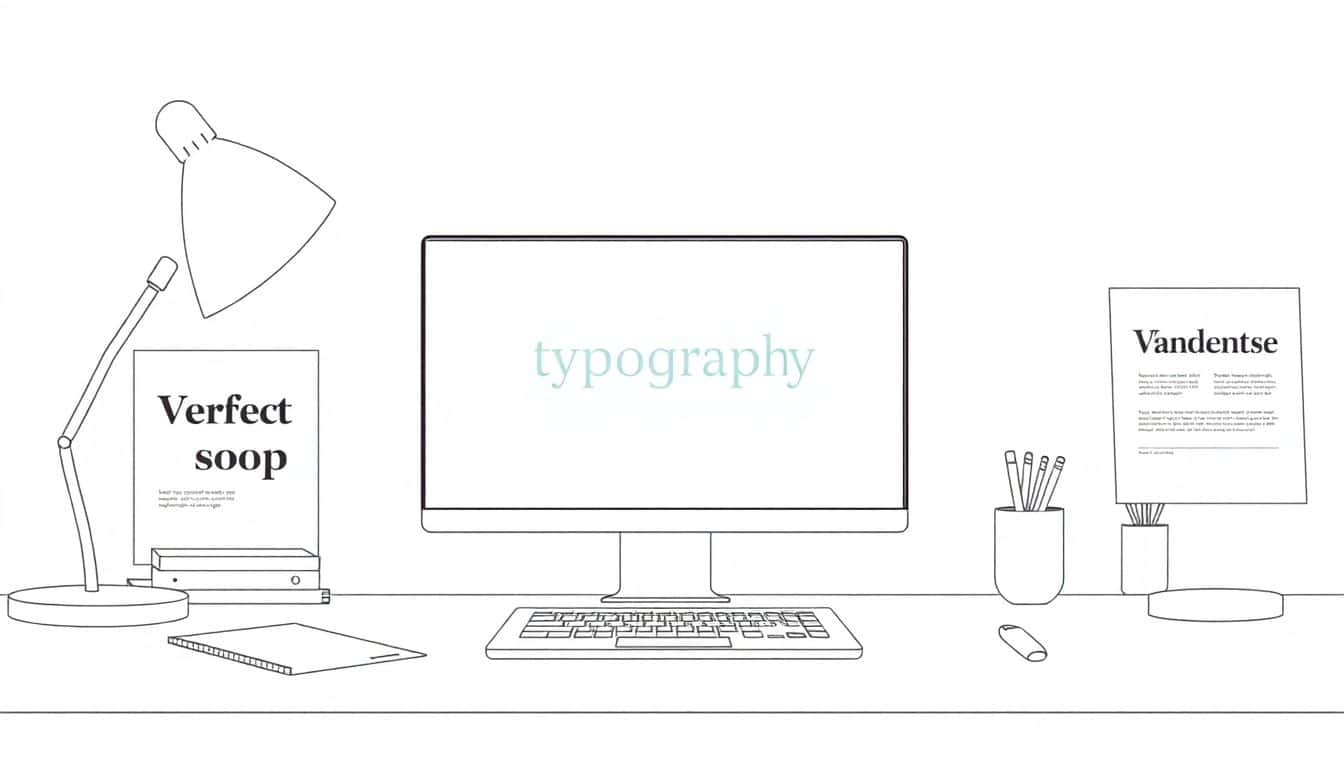
Evitar errores tipográficos comunes puede marcar una gran diferencia en cómo se percibe tu contenido y cuán fácil es de leer. Aquí tienes una guía rápida y directa para ayudarte a detectar y corregir estos problemas antes de que hagan que los lectores abandonen.
1. Limita la cantidad de fuentes utilizadas
Usar demasiadas fuentes en una sola página crea caos y distrae a los lectores. Mantener entre 2 y 3 fuentes mantiene tu diseño limpio y profesional. Por ejemplo, podrías usar una para encabezados y otra para el cuerpo del texto, pero evita una fuente nueva para cada sección. La investigación muestra que una tipografía deficiente, incluido el uso excesivo de fuentes, hace que el 38% de las personas deje de interactuar con un sitio web [fuente](https://automateed.com/why-is-grammarly-so-expensive-an-in-depth-analysis/).
2. Empareja fuentes con cuidado
Al elegir fuentes que combinen entre sí, el contraste es clave. Combina una fuente serif (como Times New Roman) con una fuente sans-serif (como Arial) para claridad e interés visual. Asegúrate de que las fuentes se complementen entre sí y no choquen. Si estás atascado, busca combinaciones de fuentes recomendadas por expertos, como las de [las mejores fuentes para cubiertas de libros](https://automateed.com/best-fonts-for-book-covers/).
3. Crea una jerarquía clara
Guía a tus lectores a través de tu contenido con una jerarquía tipográfica. Utiliza fuentes más grandes y en negrita para los encabezados, ligeramente más pequeñas para los subtítulos y un tamaño cómodo para el texto de párrafo. Esto ayuda a evitar confusiones y mantiene la página organizada. Cuando la jerarquía es clara, los lectores saben qué leer primero y qué es lo más importante.
4. Usa la alineación de texto adecuada para la legibilidad
El texto alineado a la izquierda es el más fácil de leer, especialmente para contenidos más largos. El texto centrado o justificado puede verse elegante pero podría provocar espaciados desiguales, lo que dificulta seguirlo. Una alineación consistente crea un aspecto ordenado y profesional y mejora la legibilidad en todos los dispositivos.
5. Ajusta el espaciado de letras (kerning y tracking)
Si las letras quedan demasiado juntas o demasiado separadas, pueden dificultar la lectura. Ajusta el kerning (espacio entre pares de letras específicos) para corregir huecos incómodos, y establece un tracking (espacio general entre las letras) adecuado para mejorar el flujo. Por ejemplo, aumentar ligeramente el tracking en los encabezados puede hacer que el texto destaque sin parecer abarrotado.
6. Establecer el interlineado adecuado
En páginas saturadas, las líneas que quedan demasiado juntas cansan la lectura. Por el contrario, demasiado espacio rompe el flujo. Una regla práctica es fijar el interlineado entre aproximadamente 1.2 y 1.5 veces el tamaño de la fuente. Esto proporciona suficiente espacio de respiración sin perder la conexión entre las líneas. Un espaciado adecuado es especialmente crucial para pantallas móviles, donde la legibilidad cae rápidamente si las líneas quedan demasiado apretadas.
Dominar estos fundamentos puede mejorar considerablemente la apariencia y la claridad de tu contenido. Recuerda: una buena tipografía no se trata solo de estética; se trata de hacer que tu mensaje sea fácil de consumir. Mantén tus elecciones tipográficas simples, contrástalas con sabiduría y establece una estructura clara, para que tu audiencia permanezca más tiempo.
7. Asegura un alto contraste entre el texto y el fondo
Tener un buen contraste es clave para asegurar que tu texto sea legible. El texto gris claro sobre un fondo blanco es un error común, ya que fatiga la vista. Opta por texto negro o de color oscuro sobre fondos claros, o viceversa, para maximizar la legibilidad. Un consejo rápido es usar herramientas en línea como [Verificador de Contraste WebAIM](https://webaim.org/resources/contrastchecker/) para verificar tus elecciones de color. Recuerda que el 38% de las personas dejará de interactuar si el diseño de tu contenido no es atractivo, y un bajo contraste juega un papel importante en ello (Adobe, 2023). Si diseñas para móvil, prueba tu contraste en diferentes pantallas para detectar posibles problemas.
8. Elige tipografías que soporten múltiples idiomas y necesidades futuras
Anticipa el futuro eligiendo tipografías que soporten distintos idiomas, caracteres especiales y diversos sistemas de escritura. Por ejemplo, si planeas ampliar tu base de lectores a nivel mundial, opta por tipografías como **Roboto** o **Noto Sans**, que soportan numerosos idiomas, haciendo tu contenido más inclusivo. Además, considera la longevidad de la tipografía; ¿se verá bien en diferentes formatos o tamaños más adelante? Esto evita que tengas que cambiar de tipografía más adelante, ahorrando tiempo y manteniendo la coherencia. Para más consejos, consulta [las mejores tipografías para portadas de libros](https://automateed.com/best-fonts-for-book-covers/).
9. Evita viudas, huérfanos y ríos tipográficos en el texto
Viudas, huérfanos y ríos son problemas tipográficos comunes que distraen y frustran a los lectores. Una viuda es una palabra única al final de un párrafo, un huérfano es una sola línea al inicio de una nueva página o columna, y los ríos son huecos grandes que recorren el texto justificado. Para evitarlo, ajusta la configuración de párrafos, la hifenación y el espaciado. Por ejemplo, ajustar manualmente los saltos de línea o usar funciones del software puede ayudar a mantener el flujo suave. Recuerda, un diseño de texto limpio mantiene a tus lectores interesados y mejora la legibilidad en general.
10. Usa un estilo consistente para viñetas, listas y avisos
Usar un estilo consistente para listas, viñetas y avisos ayuda a que tu contenido se vea organizado y profesional. Decide si usas círculos, cuadrados o guiones, y mantén esa elección a lo largo de todo el documento. Además, mantén la indentación y el espaciado uniformes para evitar una apariencia desordenada. La consistencia en el estilo guía la mirada de tus lectores y garantiza que comprendan y recuerden fácilmente los puntos clave. Por ejemplo, si estás destacando consejos para escritores, un formato coherente hace que tu consejo sea más claro y memorable.
Preguntas frecuentes
Usar demasiadas tipografías puede hacer que tu diseño se vea recargado y confuso. Limitar las tipografías crea una apariencia más limpia y ayuda a mantener la armonía visual, asegurando que tu mensaje sea claro y fácil de leer.
Elige fuentes que se complementen entre sí en estilo, peso y ambiente. Busca un contraste claro con diferencias marcadas, pero mantén la armonía para un aspecto profesional y cohesivo.
Crear una jerarquía clara mediante el tamaño y el peso de la fuente, alinear el texto correctamente y usar un espaciado entre líneas adecuado. Un alto contraste entre el texto y el fondo también facilita la legibilidad.
La alineación adecuada mejora la estructura y el flujo de tu texto, facilitando que los lectores escaneen y comprendan tu contenido. Una alineación consistente mejora la coherencia visual general.